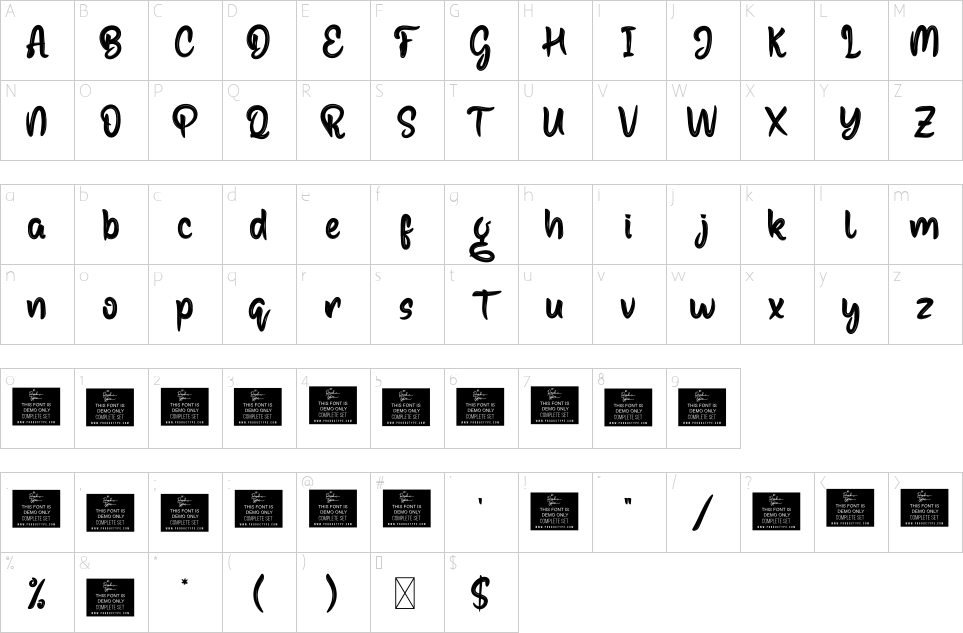
A Basting Font é uma elegante opção para designers que buscam uma tipografia fluida e versátil. Desenvolvida pelo produtype, essa fonte foi projetada com um estilo moderno e minimalista que se adapta perfeitamente a várias aplicações digitais, desde textos profissionais até design gráfico de moda. Com sua simplicidade clara e seu equilíbrio harmônico, Basting é uma escolha segura para quem busca elegância em cada caractere impresso ou digitalizado. É disponível tanto para sistemas Windows quanto Mac, tornando-se uma fonte versátil que complementa os esforços de qualquer designer gráfico. A Basting Font é uma excelente opção para aqueles que buscam uma tipografia clara e moderna sem comprometer a qualidade, feita para se destacar em designs simples ou complexos.